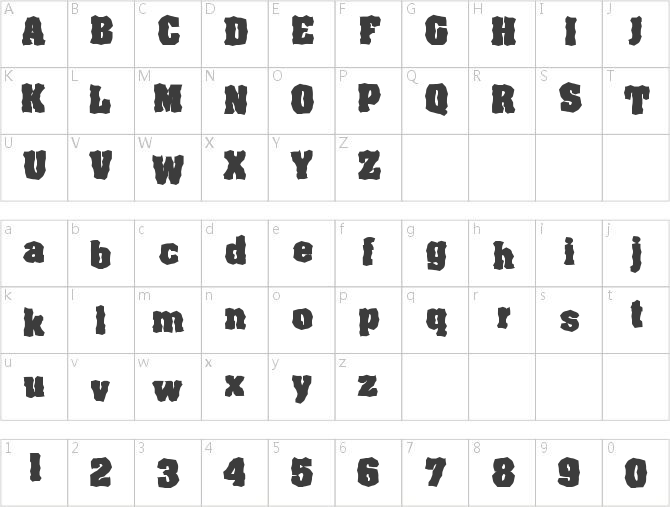
FZ WACKY 65
FZ WACKY 65介紹
FZ WACKY 65字體字庫(kù)是一款讓人賞心悅目、百看不厭的英文字體,適合各類(lèi)廣告和產(chǎn)品包裝設(shè)計(jì)應(yīng)用,字體大小0.07MB,格式為ttf字體,上傳用戶(hù)是373790005,作者/版權(quán)方為未知